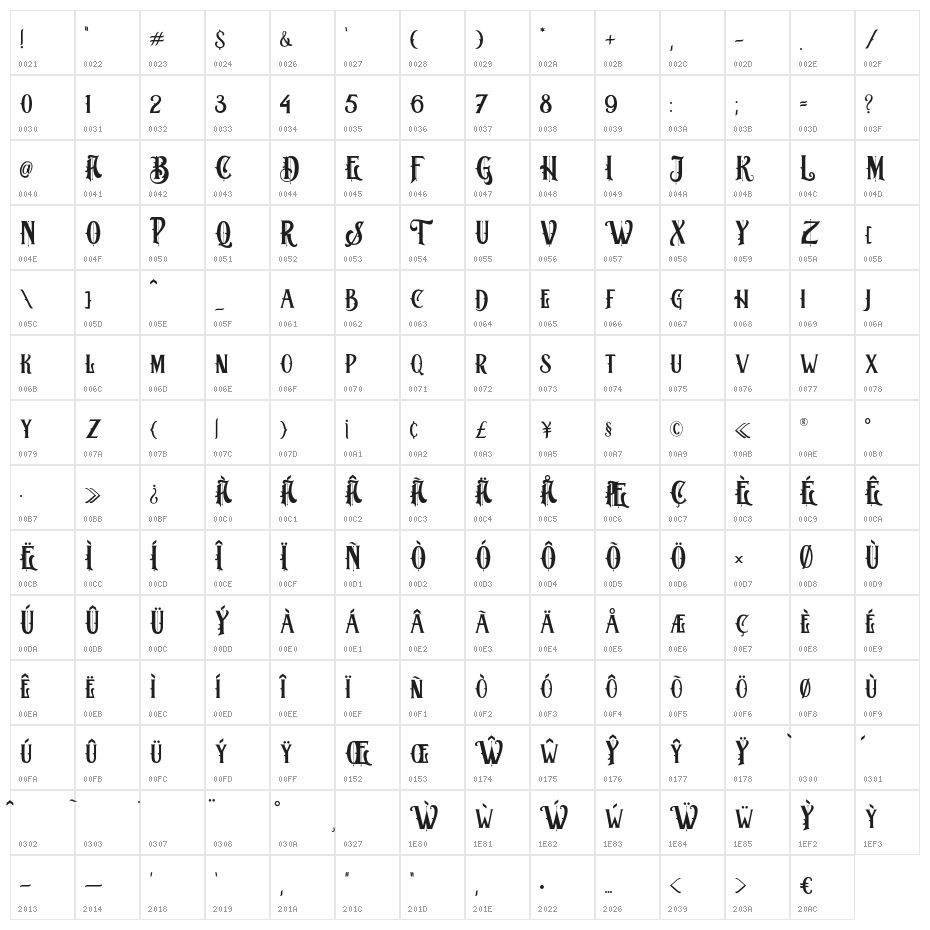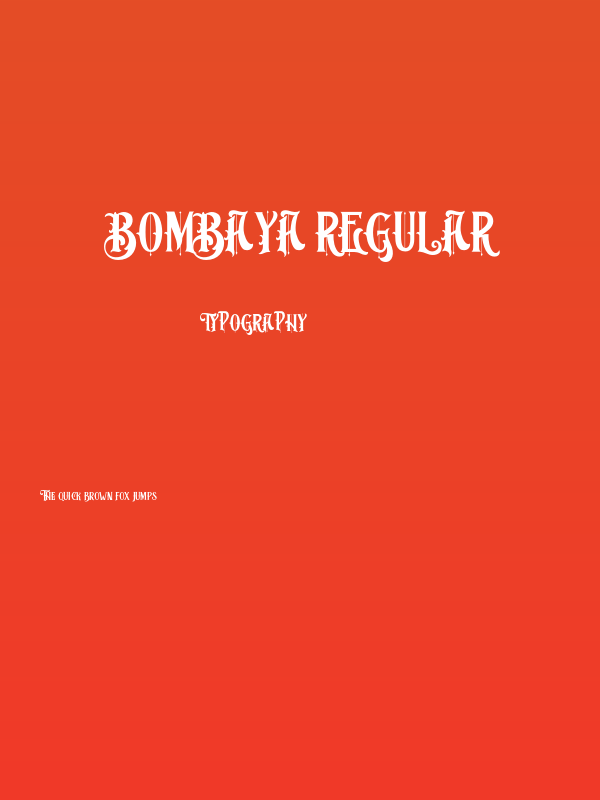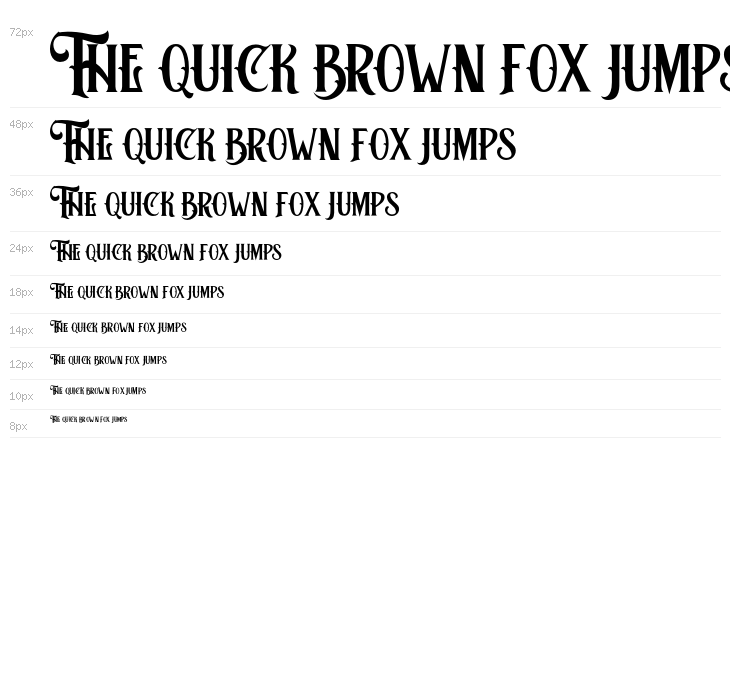
Bombaya Regular Font
✎ Gothic
| Categorie | Gothic |
| Progetti proposti | Ideal for branding, poster design, album covers, and any project requiring a dramatic and elegant typeface. |